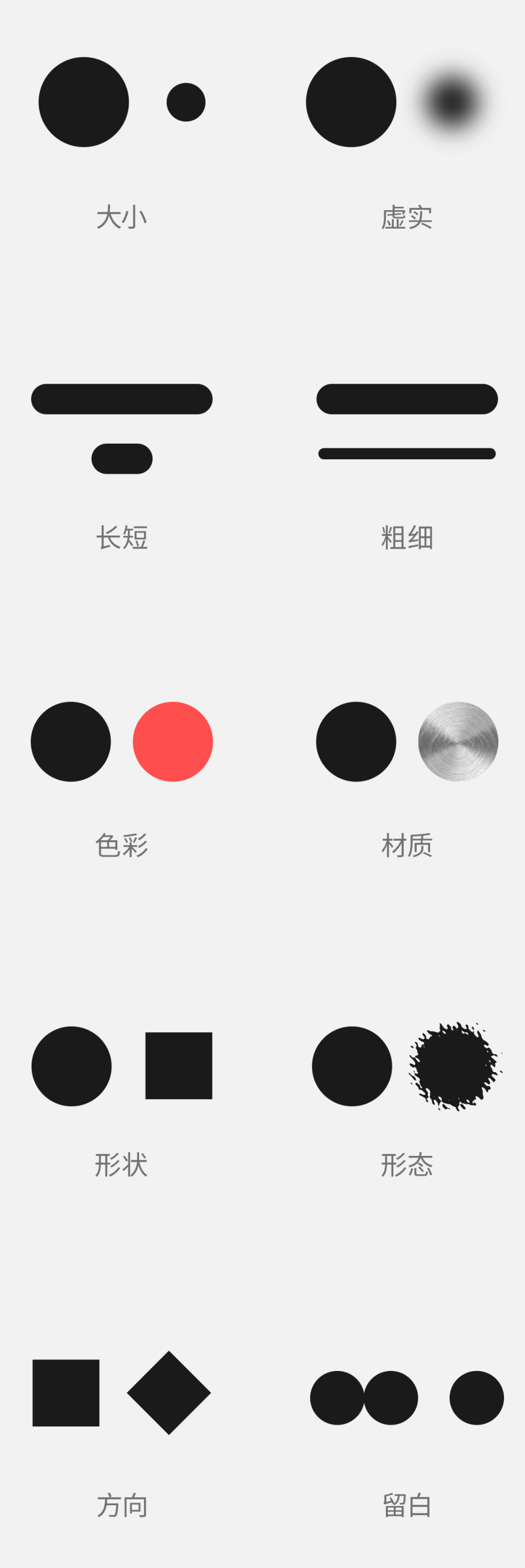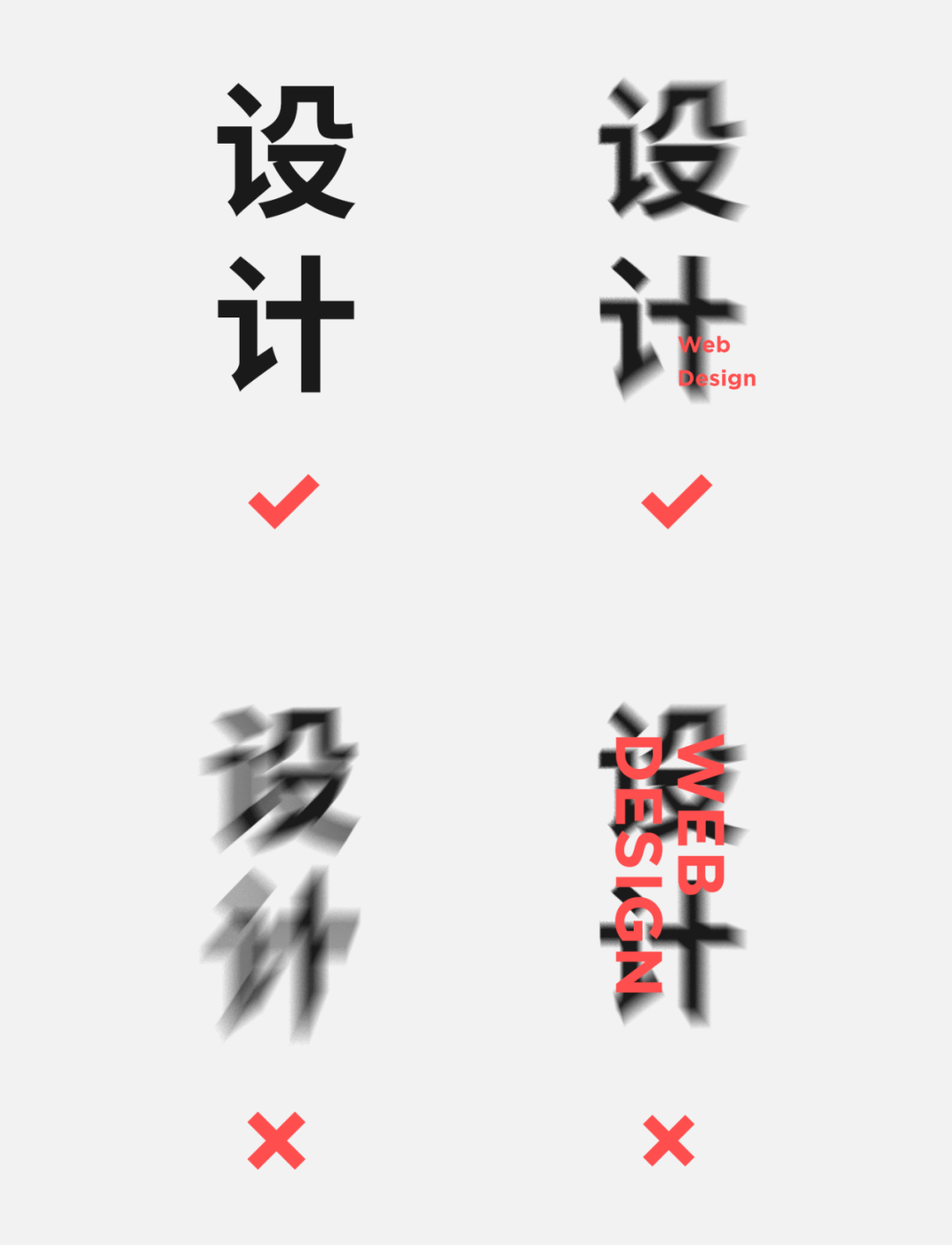
设计作品总是不够吸引眼球,应该如何解决
作为设计师,我们在工作中时常会遇到这样的情况:作品缺少层次感、画面主次不分明、版式单调、呆板、太过常规化……这也是设计工作中的痛点。做设计的同学都知道这句话,叫做:无对比不设计。虽然很多人都知道对比在设计中的重要程度,但在工作中却还是会出现前面所说的那些问题。所以本期的内容就以对比作为切入点,解决上面所说的问题。通俗一点来讲,对比就是一个元素与另外其他元素相互比较的设计手法,通过营造视觉元素之间的差异化,从而制造视觉冲突。1. 对比不够明朗:这也是很多新手设计师会犯的失误,明明使用了对比,但差异化的体现总是似有非有,不够直观。下面看个错误的案例:2. 对比缺少目的性:尤其是当画面元素多时,这也想强调那也想强调,结果导致画面缺少主次关系、元素与元素之间相互抢。对比的重点在于:你想要强调的元素是什么,就通过对比的手法让他跟其他元素形成视觉上的明显差异化。
你有没有想过,在设计工作中,运营和老板常说的:放大、标红、加粗具体指的是什么?
对比是不可或缺的重要设计手法之一,可以说只要是设计师,就离不开对比。那么该有人问了:对比在设计中的作用有哪些?
第一:对比是信息整理的好手段,他能让用户快速分别出哪些是主要信息,哪些是次要信息,提高阅读效率。
第二:改变作品呆板、单调的视觉感受,提升画面整体的跳跃率以及层次感。
第三:强烈的对比能提升视觉冲击力,让画面更加生动、有趣。第四:对比手法还可以提升作品的出彩度,更吸引用户眼球。对比手法在设计中的具体表现形式有很多种,比如:大小、长短、粗细、颜色、材质、形态、留白、虚实、方向、透视、图文、文字、表情、年龄等等。虽然说对比手法在设计中的表现形式多种多样,但在作用及目的性上,很多也都是有共通性的,下面我们就以对比目的作为分类,逐一来说。
说到对比,最被人所熟知的作用就是突出主体,通俗点理解就是通过对比的手法让用户知道哪个是主角、哪些是配角。
不管是通过大小、长短、粗细、形态、色彩、形态等等不同的表现手法,都要确保能形成明显的视觉差异化,让元素之间互为参照物,举个简单的例子:很显然,红色色块更吸引人的眼球,也更容易引起注意,因为周围黑色色块都很雷同,没有明显的视觉冲突,而相反,红色色块与其他元素不同,差异化很强烈,所以这就是通过色彩对比的表现形式突出了主体。这里不得不提格式塔原理:人类会无意识之中,把相同形状或形状、形态相似的物品看做一个整体。对比就是利用了这个原理,制造视觉差异化,突出你想突出的视觉元素。
通过色彩对比,重点主体得到了凸显,其他视觉元素保持了相对统一,这就是对比最基本的作用。同样适用于其他表现形式:大小、促销、长短、虚实……
其实在设计中,只要恰当的使用对比手法,对于作品整体的层次感提升就有帮助,比如最简单的大小对比:
如图所示,在层级上已经算是有大有小、有主有次了,可以说是设计中最简单的层次感体现方式了。
即使最简单的对比,也能体现出视觉上的层级关系,如果是为了提升设计作品整体的层次感,那么对比可以做的更丰富一些,比如:结合大小、虚实的对比形式,对于层次感的提升会很有帮助。如图所示,虚实对比的手法让作品具备了一定空间上的前后遮挡关系,视觉层次上给人的感觉更加丰富、立体。再比如我们经常看到的产品场景图,也很喜欢使用这种虚实对比的形式展示:
虚化的视觉元素是为了体现整体的层次,实物是主体,为了突出强调的,这样就形成了虚实对比。
这里需要说一点:视觉层次感不单纯指空间维度的变化,还可以通过提升整体视觉丰富度来体现,比如下面这个案例:如上图案例所示,单纯的看左侧黑白稿,仅仅通过大小、粗细对比就让整体在视觉上很有层次感。再看右侧案例,在左侧基础上结合色彩对比的形式,使得整体层次感受更加丰富,而这种层次感就是通过视觉丰富度进行体现的。强调:对比的形式不要拘泥于某一种,可以相互结合使用,这样不管对于信息整理还是主次关系、层次感,都会起到很好的加强、辅助的作用。有些时候,作品会给人感觉很平淡、枯燥,这让很多设计师头疼,而通过对比手法就可以改善以上问题。首先简单的理解下跳跃率:版面上“大块的部分”与“小块的部分”之间的比叫做“跳跃率”,通俗一点来说:就是大块与小块之间的对比强度。如上图所示,左侧和右侧案例从设计的角度来说都很好,只是两者给人的感觉有些不同,左侧案例给人一种相对安静、统一的视觉感受。而右侧案例则通过明显的色块分割,形成了很强烈的视觉冲突,使得作品整体给人的感觉更加活跃、富有跳跃性,也更有层次感。大多数情况下可以这么理解:在视觉元素不变的情况下,对比强度越强,作品的活跃度就越大,再举个很简单的例子:虽然文案都一样,但两者给人的视觉感受却天差地别,很显然右侧作品视觉上更富有跳跃性,文字信息更有层次感。这一切都要归功于对比的手法,因为加强了对比,所以作品在视觉上给人的感受也更活跃。当你的作品总是给人很单调、呆板、平淡、缺少亮点时,不妨仔细审查一遍作品有没有做好对比?
但也要强调:作品并不是越跳跃就越好,比如一些作品本身就是想营造一种安静、统一的感觉。而像儿童节海报,整体感觉活跃一些会更好。所以一定要结合最终目的进行设计。首先我们先来说下:设计感对于作品来说有用吗?比如我们常说的点缀性的元素、英文、线条等等,其元素本身在作品中并没有太大的含义,只是起到辅助、点缀的作用。所以你可能会听到甲方或者老板问你:为什么要加英文,谁能看懂?除了填充空白的作用,还有个目的就是提升作品的设计感。举个现实中的例子:同时有两女生站在男生面前,一位普普通通,另一位肤白貌美大长腿,你会看谁多一眼?但需要注意的是:不要一味的强调设计感而忽略了目的性,设计感也许可以让你原本70分的作品向90分提升,但肯定不会将50分作品提升到70分,因为你最基本的都没做好,谈设计感就是本末倒置了。同样都是以设计二字为主体,下面两个案例就属于过分强调设计感而忽略了目的性,关键文字的识别性高于一切设计感。而上侧两个案例,相比而言,右侧在兼顾文字识别性的前提下,给人的感觉更新颖、富有层次感和设计感。
所以当标题性关键文案经特殊处理后,与常规文字就形成了对比,可以理解为对比手法中的形态对比,下面看个案例:
如图所示,案例就用到了文字之间肌理和大小的对比形式,不仅丰富了主次文案的层次,还间接的提升了作品整体的设计感。综上所述:尤其是形态、虚实、空间、图文、角度、位置此类的对比形式,对作品设计感的提升有很大帮助。多数情况下,形式感强的对比都会依附于常规对比形式之上,也就是说先要做好基础,再追求设计感。要切记:设计目的高于设计感!说到氛围感大家并不陌生,比如:对抗、活泼、有趣、激烈等等,而常用的对比手法就有提升氛围感的作用,比如:强烈的色彩对比,能体现出对抗、激烈、活泼的氛围;空间位置对比能体现出有趣……
如图所示,案例通过颜色对比的形式,即冷暖色对比,加强了作品整体的氛围感和视觉冲击力,也正因如此,使得作品给人的视觉感受更加立体。对比无处不在,往往一些很有意思的创意都来源于对比手法,只是呈现形式有所不同而已,比如:猫与虎在形态上形成了强烈的对比,作品给人的感受有趣、新颖,这就是对比所带来的氛围感受。
前面也说了,对比在一定程度上也能体现出对抗、激烈的氛围,除了被大家所熟知的冷暖色对比外,还有哪些?通过位置、表情、形态的对比,也可以体现出激烈、对抗的氛围感受。通过整篇文章你会发现,即使同样的对比手法,有时候所带给我们的视觉感受也各不相同,往往在强调某一作用时,无形之中也兼顾了另外其他的作用,比如:当对比是强调突出主体时,也兼顾了整体层次感……
所以在工作中,我们无需刻意强调哪种对比形式对应哪种作用,因为很多都是互通的,根据自己的设计目的,做到灵活使用即可。